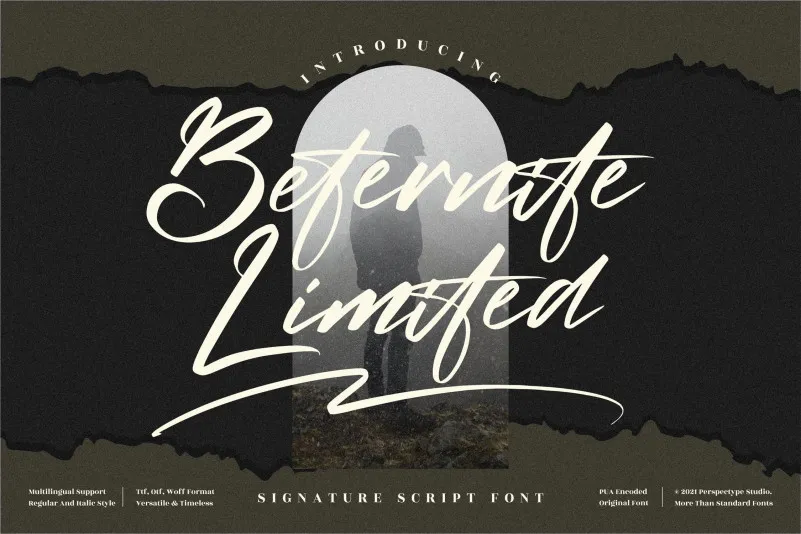
Beternite Limited Font – Download Grátis
A Beternite Limited é uma elegante fonte círbara que oferece um toque delicado e adaptável para qualquer projeto. Esta fonte script tem uma vasta gama de aplicações, tanto na criação de cartas de cumprimentos quanto no headline de manchetes noticiosas. E, sem dúvidas, vai adicioná-la um ar romântico à sua próxima tarefa visual. Se você está procurando por uma fonte script que seja suave e versátil para diversos tipos de projetos gráficos, Beternite Limited é a opção perfeita para levar um toque especial às suas criações.